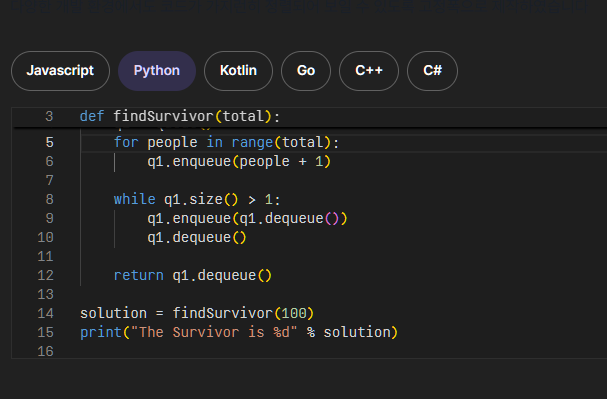
엘리스 디지털코딩체 — 엘리스에서 배포하는 무료 폰트입니다. 고정폭 구조와 둥근 고딕 형태를 결합해 코드처럼 정돈된 인상을 주는 서체
엘리스가 2021년에 내놓은 서체로, 세 벌 가운데 유일하게 용도가 아주 좁게 정해져 있습니다. 코드를 쓰기 위한 서체입니다.
무엇을 어떻게 바꿨는지 회사가 직접 설명합니다. 디지털배움체를 프로그래밍용으로 최적화한 폰트이고, 다양한 개발 환경에서도 코드가 가지런히 정렬되어 보일 수 있도록 고정폭으로 제작했다는 것입니다. 고정폭은 모든 글자의 가로 폭이 같다는 뜻입니다. i처럼 좁은 글자와 W처럼 넓은 글자가 같은 자리를 차지해야 코드의 들여쓰기와 세로줄이 어긋나지 않습니다.
굵기는 Regular와 Bold 두 가지입니다. 코드 편집기와 터미널, 개발 문서에 맞고, 반대로 **고정폭이라 일반 본문이나 제목 조판에는 맞지 않습니다.** 글자 폭이 다 같으면 낱말의 덩어리감이 사라져 읽기가 불편해지기 때문입니다. 오픈 폰트 라이선스로 배포되어 수정과 재배포가 자유롭습니다.